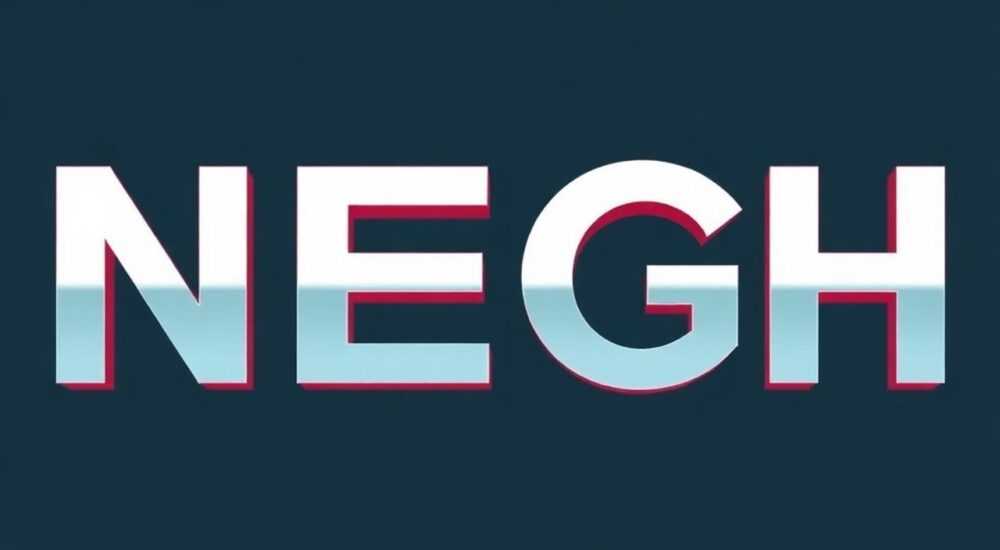
Как в фотошопе сделать жирный шрифт
В дизайне текст — это не просто информация, это мощный визуальный элемент. Часто именно жирное начертание шрифта помогает выделить заголовок, привлечь внимание к акции или усилить эмоциональное воздействие. Adobe Photoshop предоставляет множество способов сделать шрифт жирным: от простого выбора стиля шрифта до продвинутых методов с использованием обводки и наложения слоёв. Главное — понимать, какой метод подойдёт в конкретной ситуации, особенно если нужен не просто «жирный», а действительно эффектный и качественный результат.
Почему важно использовать жирный шрифт
Жирное начертание — один из ключевых инструментов типографики. Оно позволяет создать визуальную иерархию, направить взгляд пользователя на главное и улучшить читаемость композиции. В рекламе, лендингах, соцсетях и печатных материалах жирный шрифт используется повсеместно. Без него сложно представить заголовок, цену распродажи или призыв к действию.
Исследования в области юзабилити показывают, что пользователи сканируют текст, а не читают его полностью. Жирное начертание помогает им быстрее находить нужную информацию. По данным Nielsen Norman Group, правильно выделенные ключевые слова могут увеличить скорость восприятия текста на 20–30%.
Однако важно помнить: жирность должна быть уместной. Избыток жирного текста сводит на нет его выделяющую функцию. Как говорят дизайнеры: «Если всё жирное — ничто не жирное». Поэтому использование жирного шрифта должно быть продуманным и целенаправленным.
Базовые способы сделать шрифт жирным
Самый простой и правильный способ — использовать встроенный стиль «Жирный» в панели символов. Для этого:
- Выберите инструмент Текст (T) и кликните по холсту.
- Напишите нужный текст или выделите уже существующий фрагмент.
- Откройте панель «Символ» (Окно → Символ).
- В выпадающем списке стилей шрифта выберите вариант с пометкой «Bold» или «Жирный».
Если шрифт поддерживает жирное начертание, оно применится мгновенно. Но что делать, если в списке нет опции «Bold»? Это означает, что выбранное семейство шрифтов не имеет отдельного жирного стиля. В таком случае Photoshop может попытаться имитировать жирность автоматически, но результат часто выглядит размытым или искусственно.
Альтернатива — изменение параметра «Насыщенность» (Weight) в современных версиях Photoshop (особенно при работе с переменными шрифтами — Variable Fonts). Переменные шрифты позволяют плавно регулировать толщину от тонкой до жирной без переключения между файлами. Это особенно полезно при адаптивном дизайне.
Когда шрифт не имеет жирного стиля
Если шрифт не предлагает жирного варианта, Photoshop может применить искусственное утолщение через пункт «Псевдо-жирный» (Fake Bold). Он доступен в виде кнопки B на панели символов. Однако этот метод имеет недостатки:
- Текст становится шире, что может нарушить композицию.
- Гарантировано появление артефактов: зазубрин, неравномерной толщины штрихов.
- На маленьких размерах псевдо-жирный текст плохо читается.
Поэтому такой способ стоит использовать только в крайнем случае — например, когда нельзя заменить шрифт, а сроки поджимают.
Продвинутые методы усиления текста
Когда стандартные средства не дают желаемого результата, дизайнеры прибегают к альтернативным техникам. Они требуют больше времени, но обеспечивают высокое качество и гибкость.
Обводка (Stroke)
Один из самых популярных способов — добавление внутренней или внешней обводки. Она визуально утолщает буквы, создавая эффект жирности.
- Выделите текстовый слой.
- Нажмите на значок «fx» внизу панели слоёв.
- Выберите «Обводка» (Stroke).
- Установите положение: «Внутри» (Inside), чтобы не выходить за границы исходного текста.
- Цвет обводки — тот же, что и у текста. Размер — от 1 до 3 пикселей (зависит от размера шрифта).
Преимущество метода — полный контроль над толщиной. Недостаток — при большом значении обводки углы букв могут «залипать», теряя чёткость.
Масштабирование по горизонтали
Ещё один способ — растянуть текст по оси X. Это делается через свободную трансформацию:
- Выделите текст (Ctrl+T / Cmd+T).
- Щёлкните правой кнопкой и выберите «Масштабирование».
- Перетащите боковые маркеры, удерживая Shift для сохранения пропорций по вертикали.
- Увеличьте ширину на 110–130%, в зависимости от эффекта.
- Подтвердите изменения (Enter).
Результат — более массивный, «жирный» вид. Но будьте осторожны: такой подход искажает форму букв, особенно в шрифтах с выраженной характерностью (например, рукописные или декоративные).
Наложение эффектов: Заливка и Тень
Для создания объёмного жирного текста можно использовать комбинацию эффектов:
- Добавьте наложение цвета (Color Overlay) с тем же цветом, что и текст, но немного увеличьте непрозрачность.
- Примените мягкий эффект «Внутренняя тень» (Inner Shadow) с нулевым смещением и небольшим размытием (1–2 px).
- Это визуально «утяжеляет» текст, делая его плотнее.
Такой приём часто используют в логотипах и заголовках для соцсетей.
Качество |
Гибкость |
Рекомендуемый размер текста |
Настоящий жирный стиль |
★★★★★ |
★★★☆☆ |
Любой |
Псевдо-жирный (Fake Bold) |
★★☆☆☆ |
★★★★☆ |
Средний и крупный |
Обводка (внутри) |
★★★★☆ |
★★★★★ |
Средний и крупный |
Горизонтальное масштабирование |
★★★☆☆ |
★★★★☆ |
Крупный |
Эффекты наложения |
★★★★☆ |
★★★★★ |
Крупный, заголовочный |
Даже опытные дизайнеры иногда допускают типичные ошибки при работе с жирным текстом. Вот основные из них:
- Использование Fake Bold на мелком тексте. На малых размерах (менее 14 pt) искусственное утолщение делает буквы слипшимися. Решение — заменить шрифт или увеличить размер.
- Чрезмерная обводка. Обводка в 5 пикселей на тексте 20 pt выглядит как рамка, а не жирность. Оптимально — 1–2 px.
- Искажение формы через масштабирование. Шрифт «Times New Roman» при растяжении становится похож на «Arial Black», но теряет элегантность. Используйте только при необходимости.
- Отсутствие контраста с обычным текстом. Если весь текст жирный, глаз не знает, на чём остановиться. Применяйте жирность точечно — для акцентов.
Как проверить качество жирного текста
Перед финализацией макета выполните быстрый чек-лист:
- Увеличьте масштаб до 200% — нет ли артефактов, зазубрин, размытости?
- Проверьте текст на фоне: хорошо ли он читается при различном освещении?
- Сравните с оригинальным жирным шрифтом (если есть): выглядит ли естественно?
- Получился ли нужный визуальный вес без потери читаемости?
Она также отмечает, что в 2025 году наблюдается возврат к качественной типографике. Клиенты и платформы (особенно Apple и Google) требуют высокой читаемости и доступности. Искусственное утолщение текста может нарушить стандарты WCAG по контрасту и читаемости.
Сделать жирный шрифт в Photoshop можно множеством способов — от простого выбора стиля до сложных комбинаций эффектов. Однако ключ к успеху — не в технике, а в понимании цели. Жирность должна служить читаемости, иерархии и эстетике, а не быть просто «толще».
- Приоритет — настоящий жирный стиль шрифта, а не искусственное утолщение.
- Обводка и эффекты дают гибкость, но требуют аккуратности.
- Избегайте Fake Bold на малом тексте и в финальных макетах.
- Всегда проверяйте читаемость и контраст жирного текста.
- Следите за трендами: переменные шрифты — будущее гибкой типографики в Photoshop.